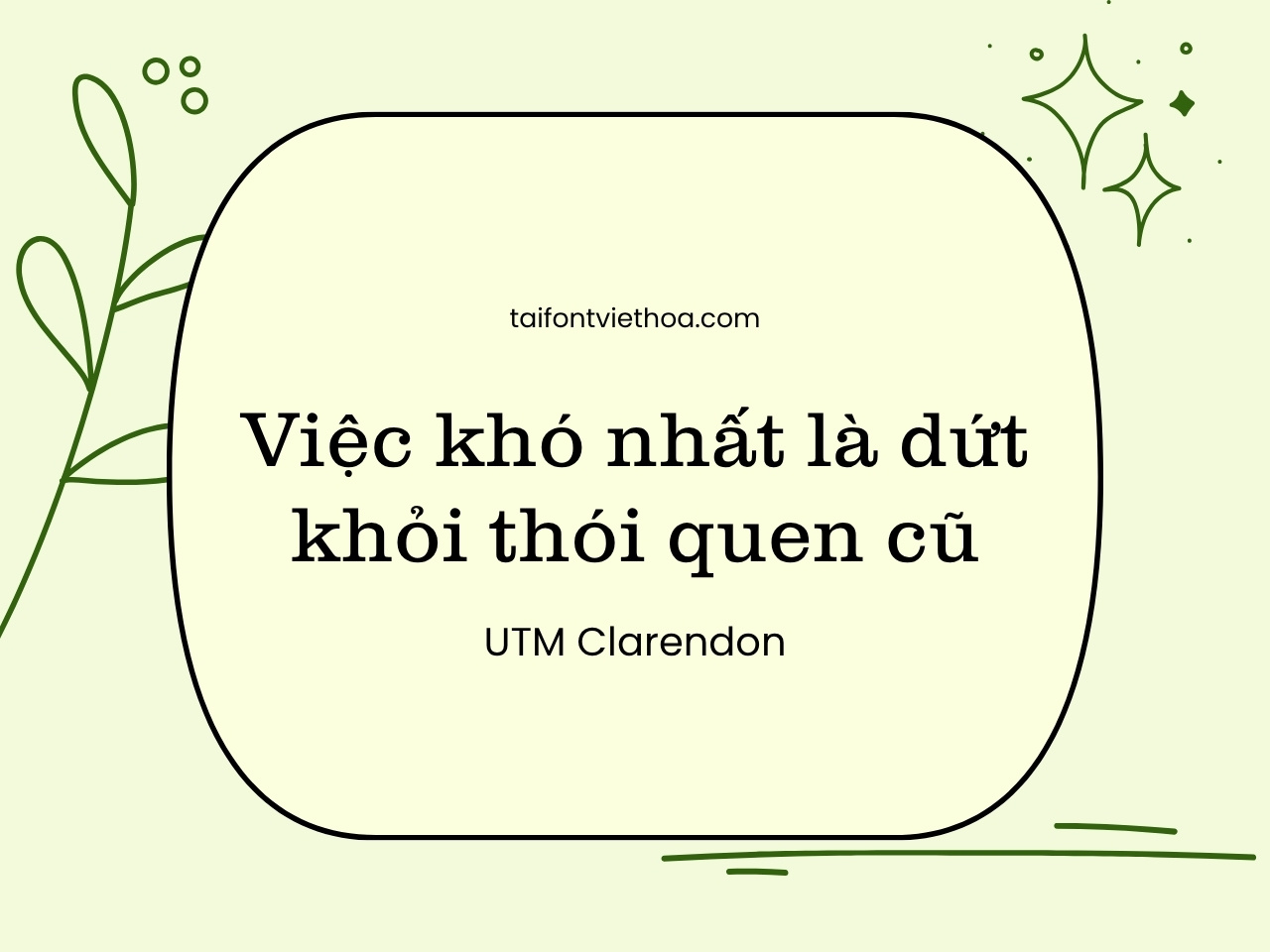
Giới thiệu về font UTM Clarendon
UTM Clarendon là phiên bản Việt hóa của font Clarendon – một kiểu chữ slab serif cổ điển, mạnh mẽ và dễ nhận diện, được thiết kế vào thế kỷ 19 và nổi bật với các nét chữ có chân dày, vuông vức và tỉ lệ cân đối. Font gốc được sử dụng rộng rãi trong các thiết kế in ấn, bảng hiệu và quảng cáo nhờ tính năng nổi bật và dễ đọc. Phiên bản Việt hóa đã được hoàn thiện để hỗ trợ đầy đủ tiếng Việt cùng hơn 200 ngôn ngữ khác, mở rộng khả năng sử dụng trong các dự án thiết kế đa dạng.
Font UTM Clarendon được taifontviethoa.com sưu tầm và chọn lọc kỹ lưỡng nhằm phục vụ cộng đồng thiết kế Việt Nam. Phiên bản Việt hóa giữ nguyên sự mạnh mẽ và rõ ràng của bản gốc, đồng thời tối ưu khả năng hiển thị tiếng Việt, rất phù hợp cho các dự án thương hiệu, quảng cáo và truyền thông số.
Đặc điểm thiết kế và ứng dụng của UTM Clarendon
UTM Clarendon sở hữu cấu trúc slab serif với các nét chữ dày, chân chữ vuông vức và độ tương phản cao. Font có thiết kế chắc chắn, tạo hiệu ứng thị giác mạnh mẽ và dễ đọc, phù hợp cho tiêu đề, bảng hiệu và các thiết kế cần sự nổi bật. Font còn trang bị nhiều ligature và glyph thay thế giúp tăng tính linh hoạt trong thiết kế.
Font thích hợp sử dụng trong thiết kế poster, bảng hiệu, nhận diện thương hiệu, quảng cáo và các dự án truyền thông đa phương tiện. Các ngành nghề phù hợp gồm: quảng cáo, thời trang, công nghệ, sự kiện và truyền thông sáng tạo.